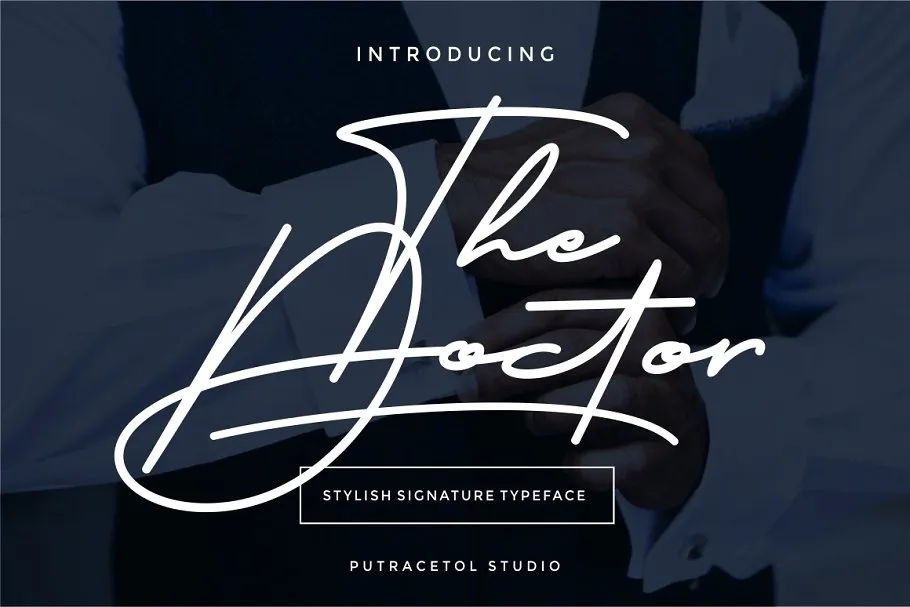
The Doctor Signature Font – Fonte Grátis
The Doctor Signature Font
A fonte The Doctor Signature Font é perfeita para designers que buscam uma solução versátil para assinaturas criativas. Com seu script elegante e sofisticado, a The Doctor Signature Font transmite um visual natural e amigável, ideal para projetos diversos em sua biblioteca de recursos gráficos. Desenvolvida pelo designer M.0Type, esta fonte é perfeitamente adequada para assinaturas digitais, cabeçalhos, etiquetas, cartões de convite, embalagens de produtos, logotipos e até mesmo mensagens em redes sociais. Com alternativas únicas que permitem um uso continuado ao longo da sua carreira profissional, a The Doctor Signature Font é uma excelente adição para qualquer designer gráfico. Adquirir esta fonte é garantir não apenas um recurso versátil, mas também uma ferramenta poderosa para criar assinaturas personalizadas e projetos de alto nível. Com a The Doctor Signature Font, seus designs ganham destaque em cada projeto.